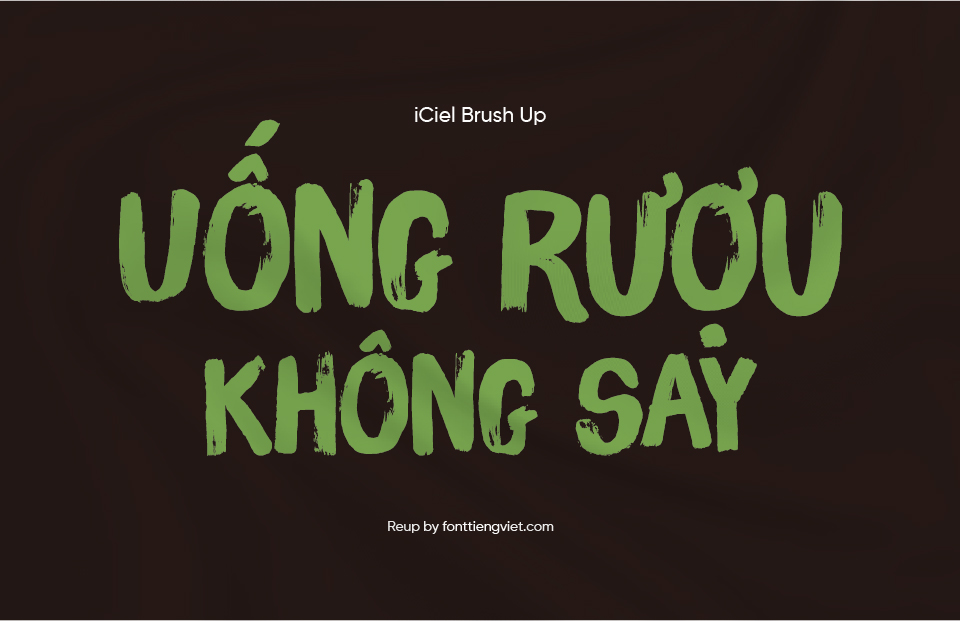
Font việt hóa iCiel Brush Up
Giới thiệu về bộ Font việt hóa iCiel Brush Up
Trong thế giới đồ họa hiện đại, việc tìm kiếm một bộ Font Miễn Phí có phong cách cá tính luôn là ưu tiên hàng đầu. Font việt hóa iCiel Brush Up là một lựa chọn tuyệt vời dành cho những ai yêu thích sự phóng khoáng và mạnh mẽ. Được thiết kế dựa trên những nét cọ vẽ tay tự nhiên, bộ font này mang đến cảm giác chân thực và đầy tính nghệ thuật cho mọi tác phẩm. Nhờ được iCiel tinh chỉnh và việt hóa hoàn thiện, người dùng tại Việt Nam có thể dễ dàng sử dụng các ký tự tiếng Việt mà không lo lỗi font hay thiếu dấu.
Ưu điểm nổi bật của Font việt hóa iCiel Brush Up
Phong cách vẽ cọ độc đáo
Đúng như tên gọi, Font việt hóa iCiel Brush Up sở hữu những đường nét thô mộc, tạo nên hiệu ứng thị giác mạnh mẽ. Các nét chữ mô phỏng hoàn hảo độ đậm nhạt của mực vẽ trên bề mặt giấy, giúp thiết kế trở nên sống động hơn. Đây là công cụ đắc lực cho các bạn học sinh khi trang trí báo tường hoặc làm Slide thuyết trình sáng tạo.
Ứng dụng đa dạng trong thiết kế
Với vẻ ngoài năng động, bộ font này cực kỳ phù hợp cho thiết kế bìa sách, poster sự kiện, logo thương hiệu hay các bài đăng trên mạng xã hội. Khả năng hiển thị rõ nét giúp thông điệp của bạn trở nên nổi bật và thu hút sự chú ý của người xem ngay từ cái nhìn đầu tiên. Sự linh hoạt này giúp các nhà thiết kế không chuyên cũng có thể tạo ra sản phẩm chuyên nghiệp.